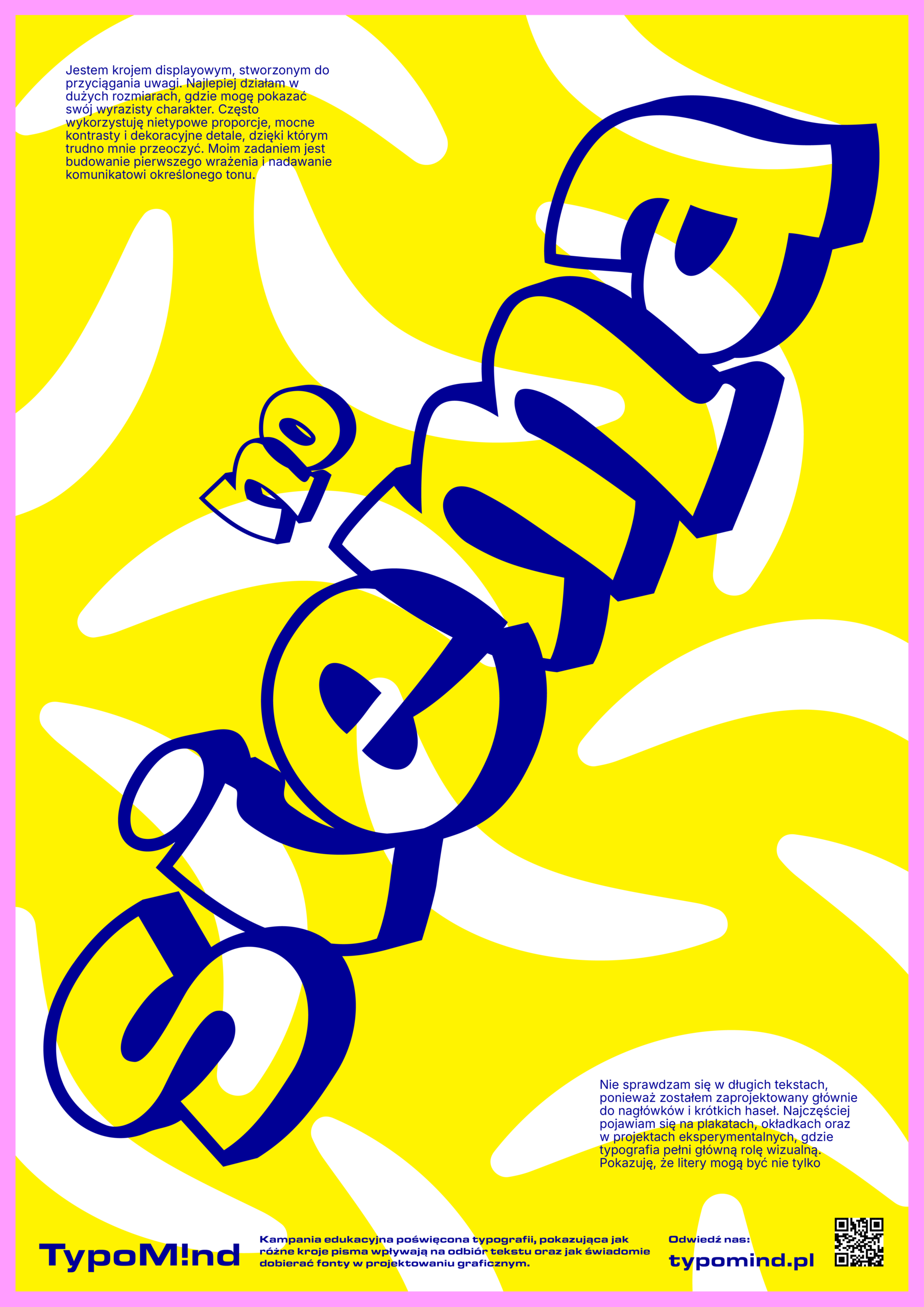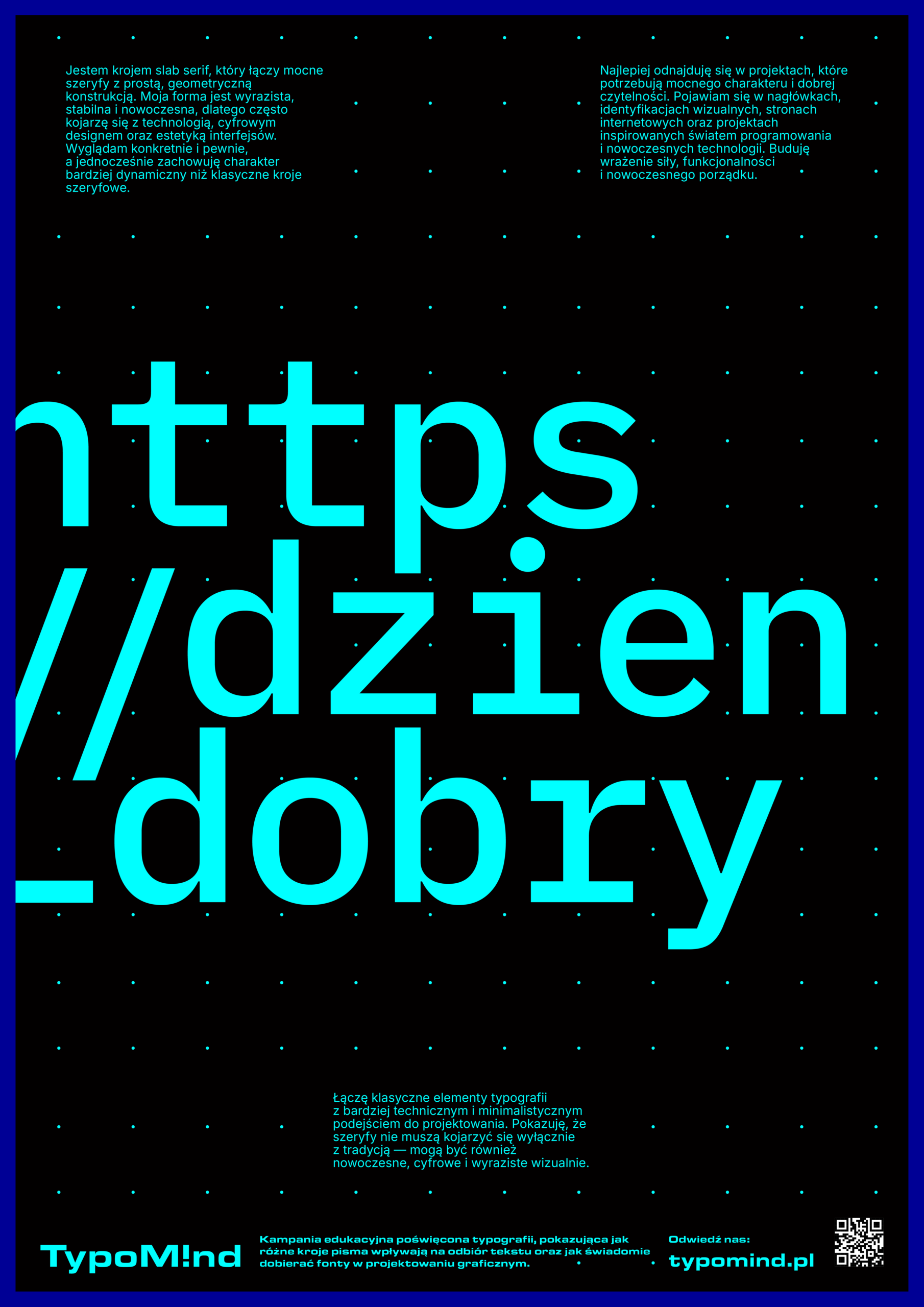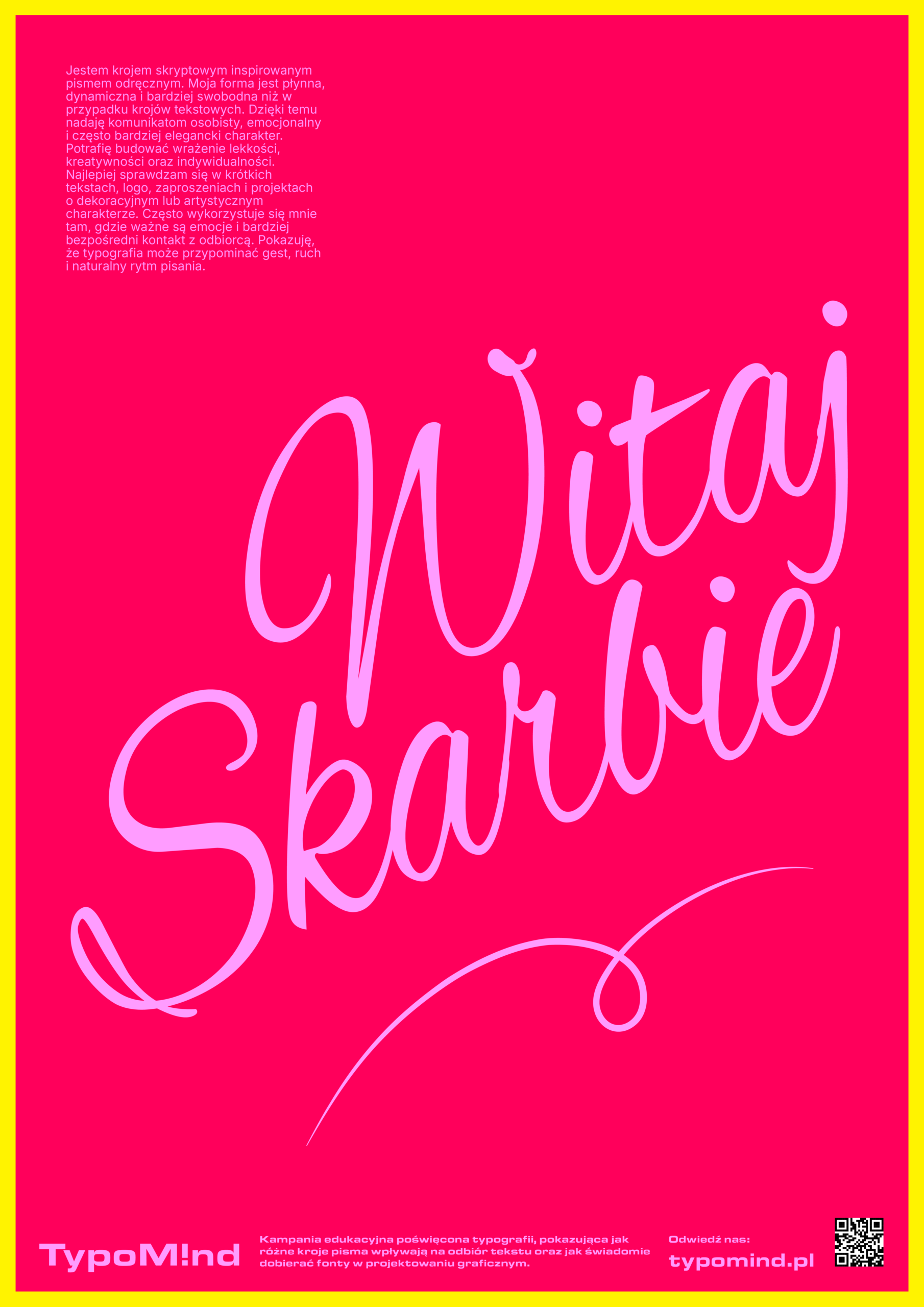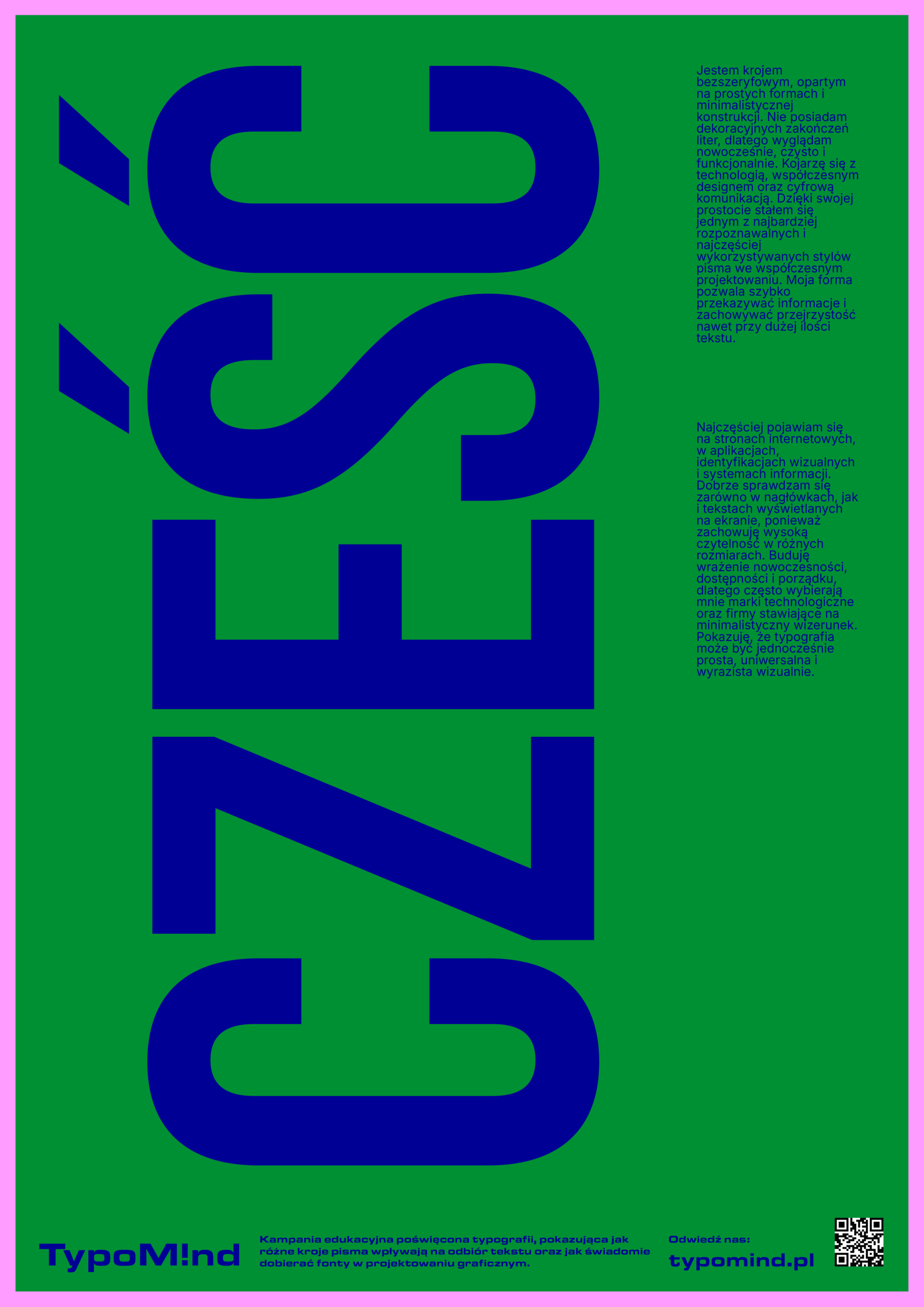
Wszystko o typografii
Odkryj moc liter
Typy krojów pisma
Przegląd najpopularniejszych stylów typograficznych
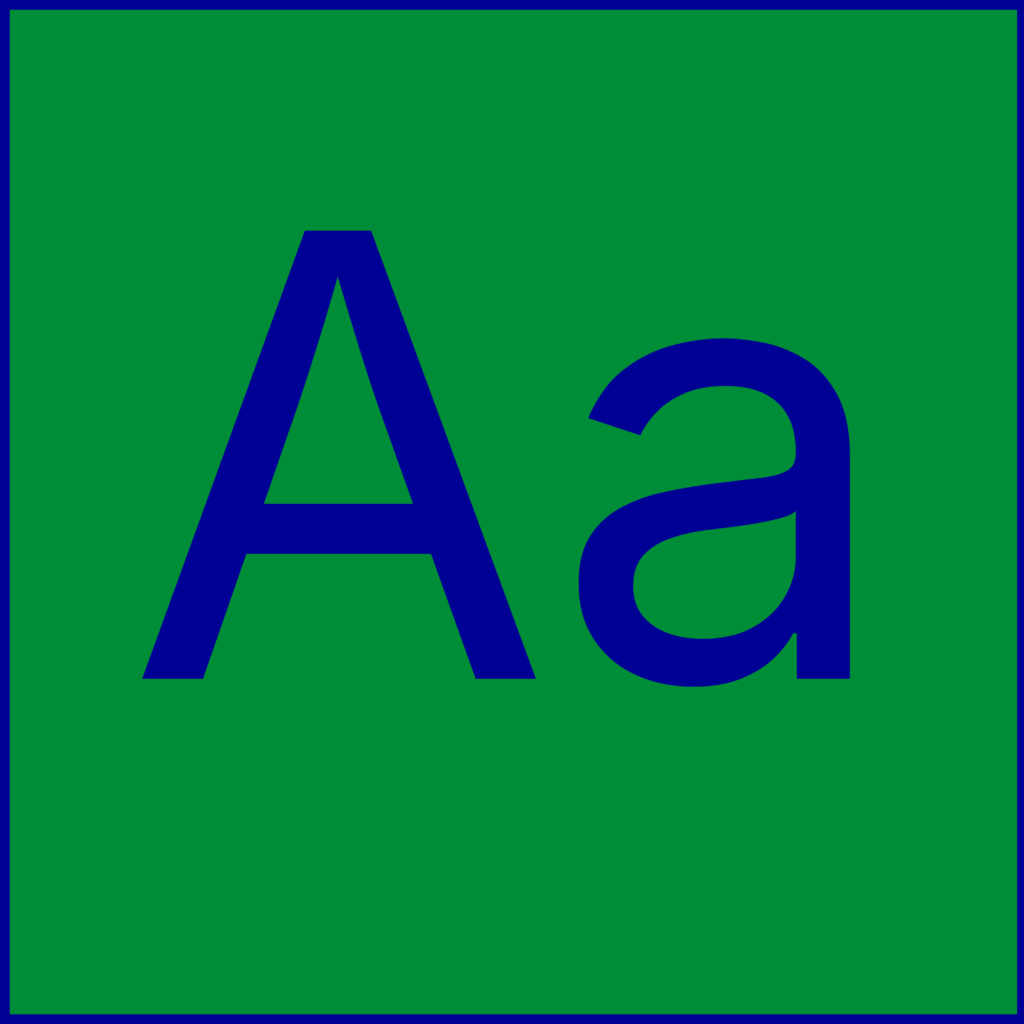
bezszeryfowe
Nowoczesne i czytelne, doskonałe do treści online.
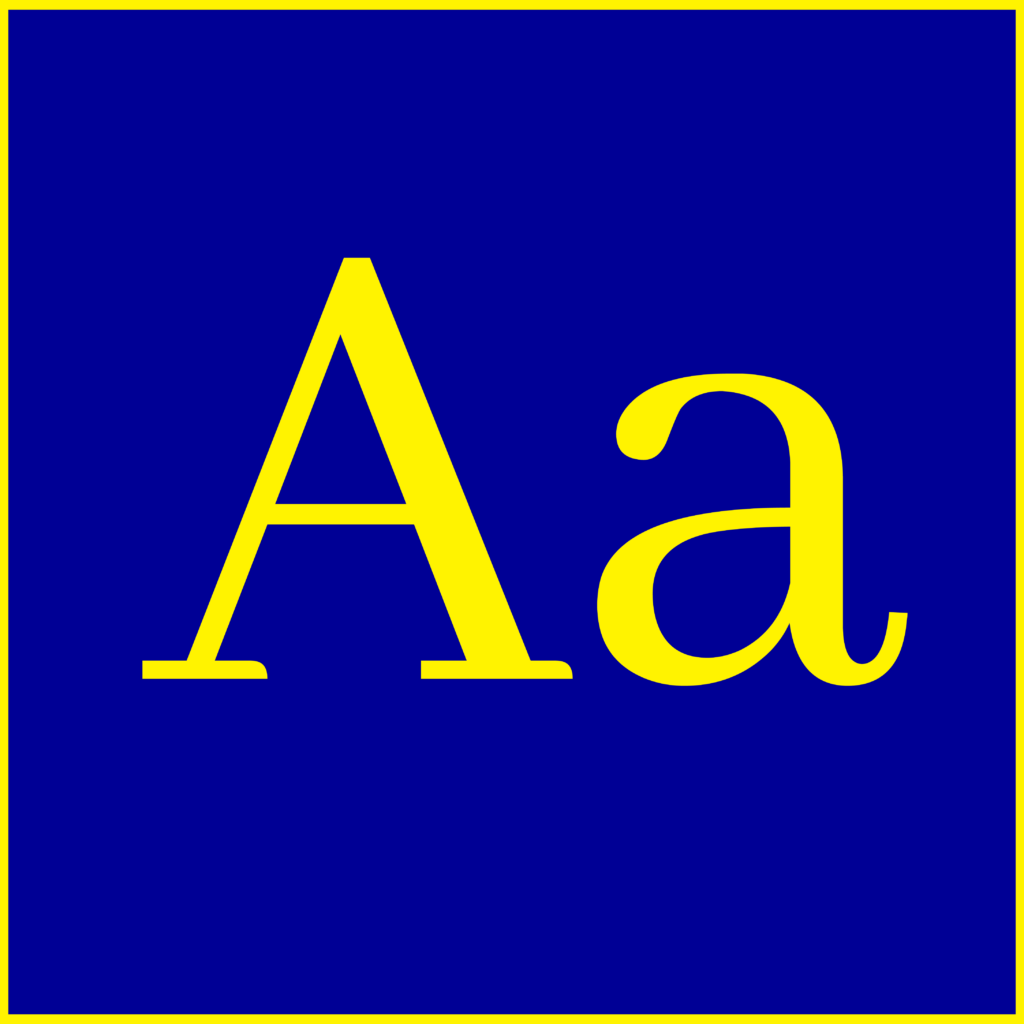
szeryfowe
Klasyczne czcionki, które dodają elegancji tekstom.
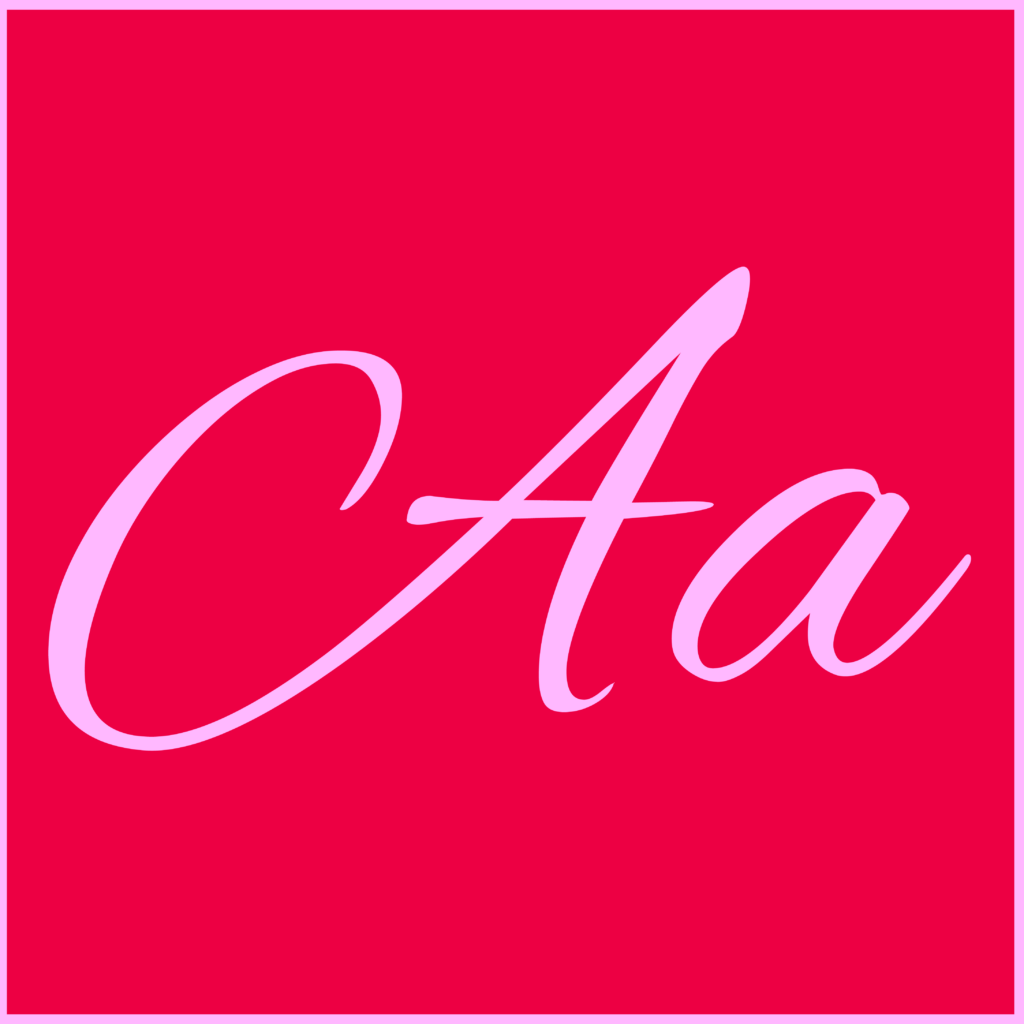
Script/pisanki
Płynne, ręcznie pisane czcionki dla osobliwego charakteru.
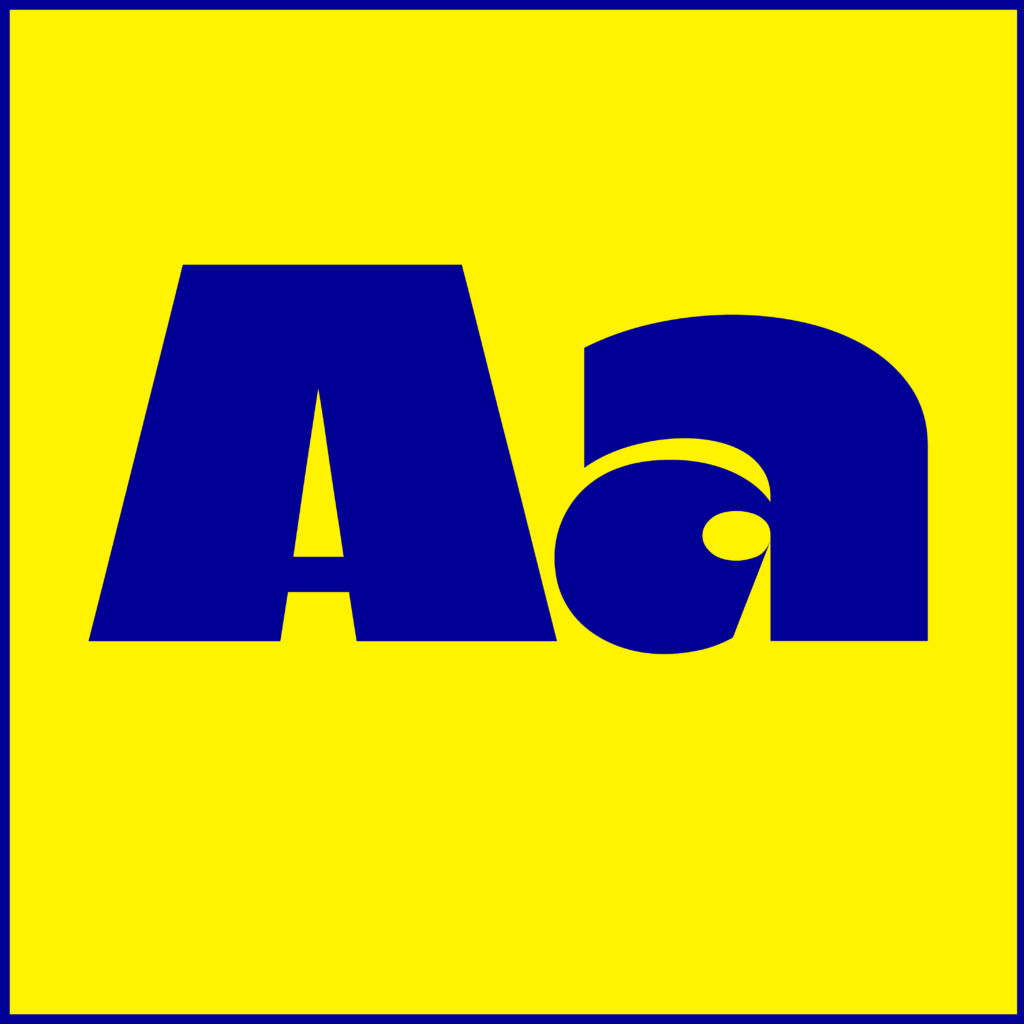
Display
Wyszukane stylizacje, które przyciągają wzrok.
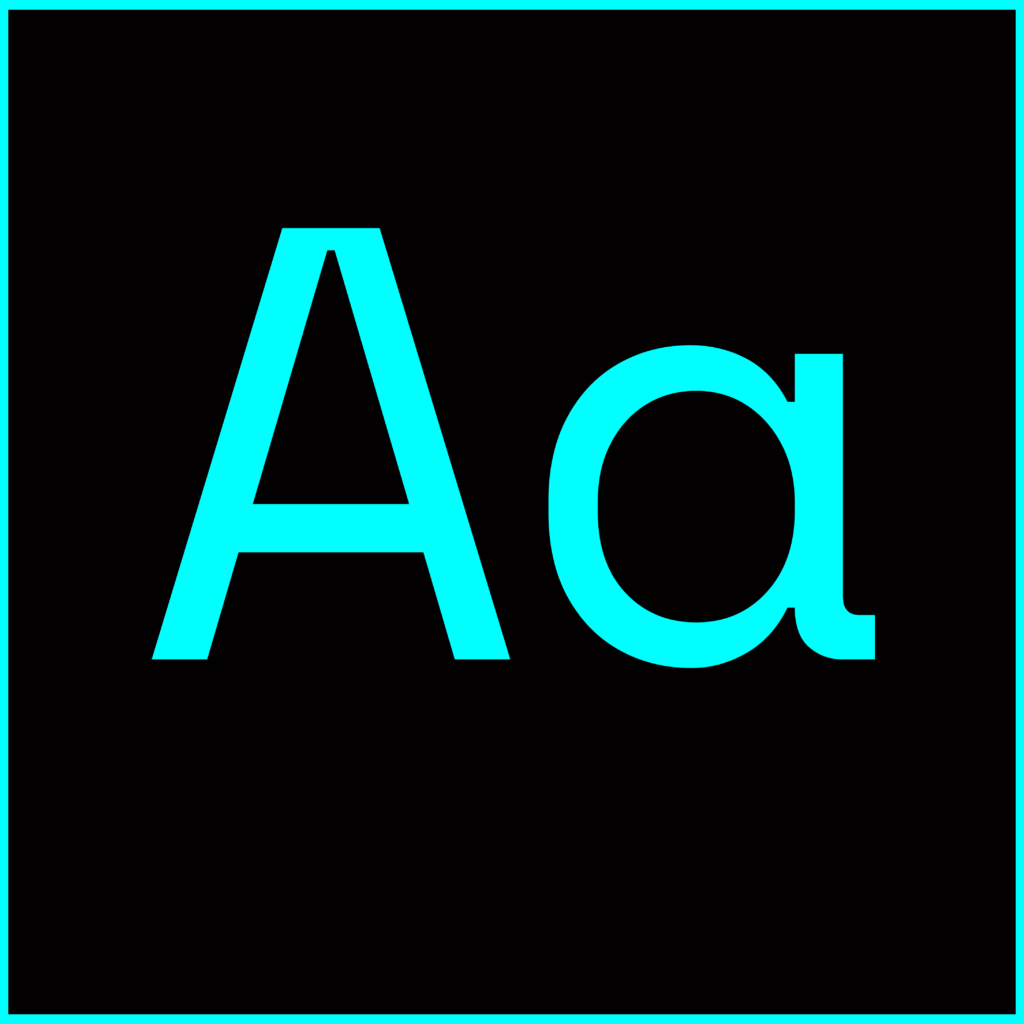
Monospace
Idealne do kodu, gdzie równa szerokość to klucz.
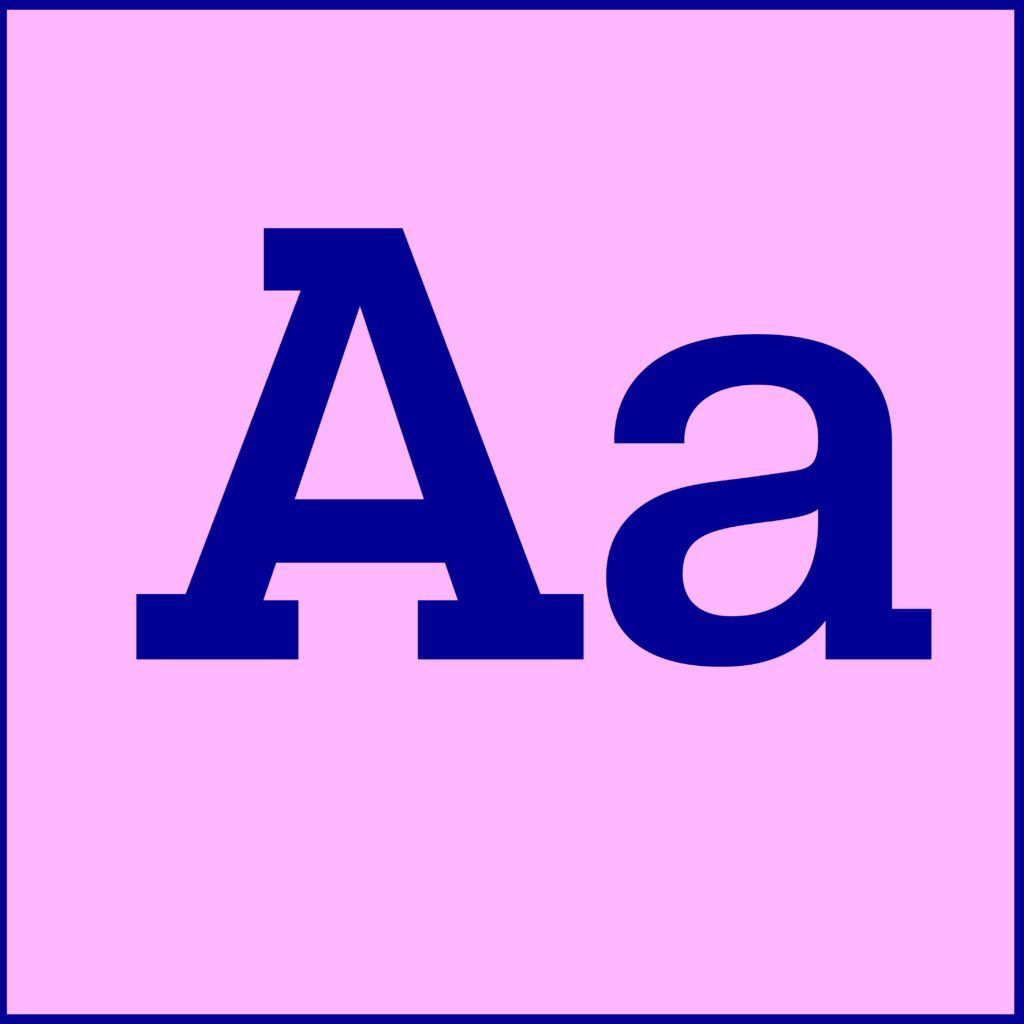
slab serif/egipcjanki
Typ pośredni z geometrycznymi, kanciastymi i pogrubionymi szeryfami. Świetnie prezentują się w nagłówkach i plakatach.
Typografia i emocje
Zrozum, jak typografia wpływa na emocje tekstu.
bezszeryfowe
Minimalizm i prostota, idealne do nowoczesnych projektów.
szeryfowe
Eleganckie i klasyczne, doskonałe dla druku.
Script/pisanki
Osobiste i artystyczne, nadające unikalny styl.
Display
Ekspresywne i przyciągające wzrok, do nagłówków.